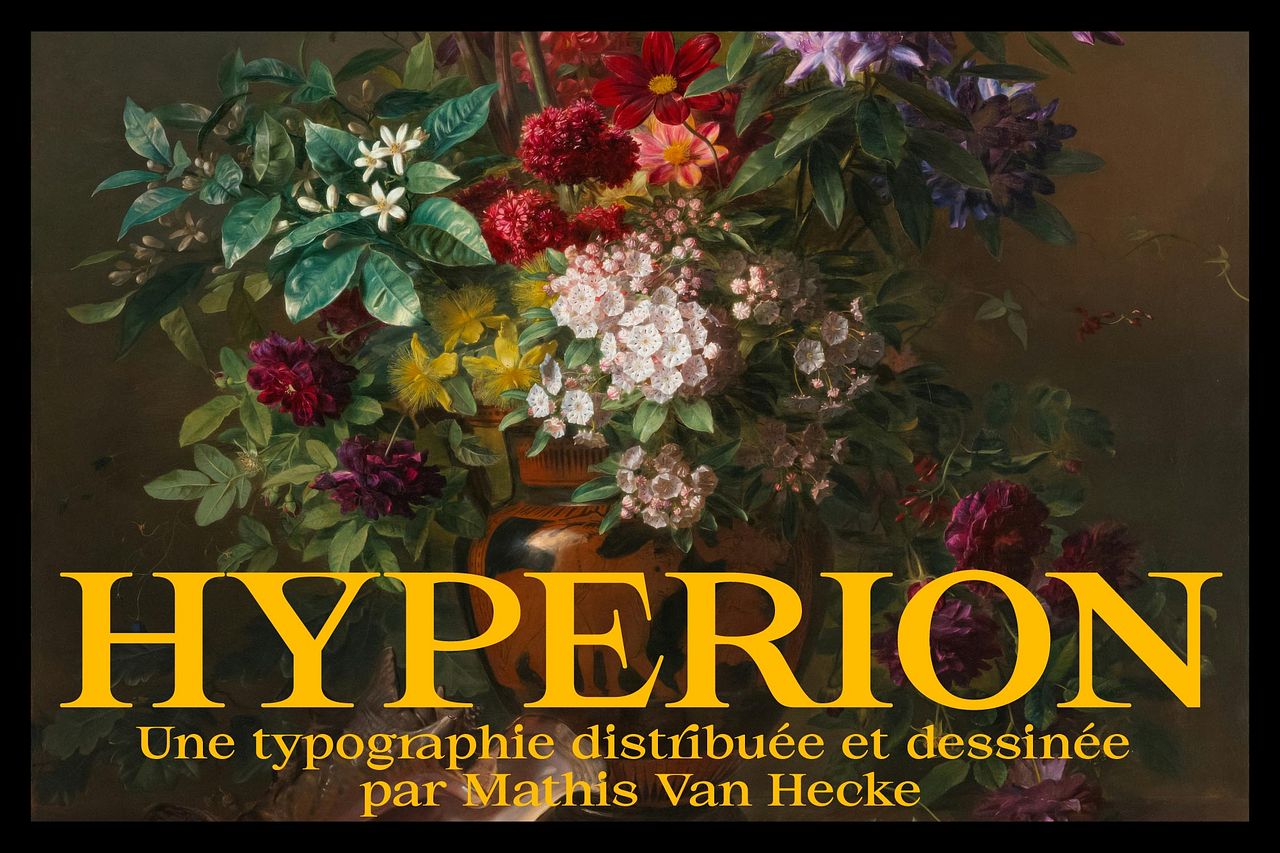
Hyperion — Typeface
Hyperion est une typographie à empattements raffinée, nommée d’après Hypérion, titan de la lumière dans la mythologie grecque. Dotée d’une prestance naturelle et d’un caractère impérial, elle a été conçue pour des projets qui souhaitent conjuguer élégance et puissance visuelle.